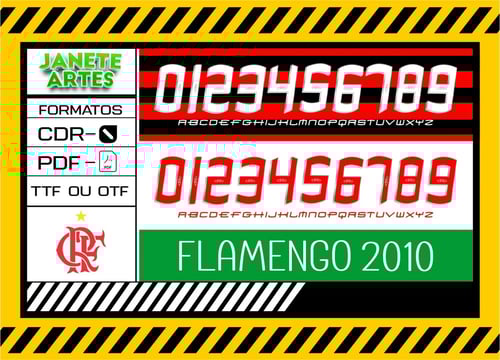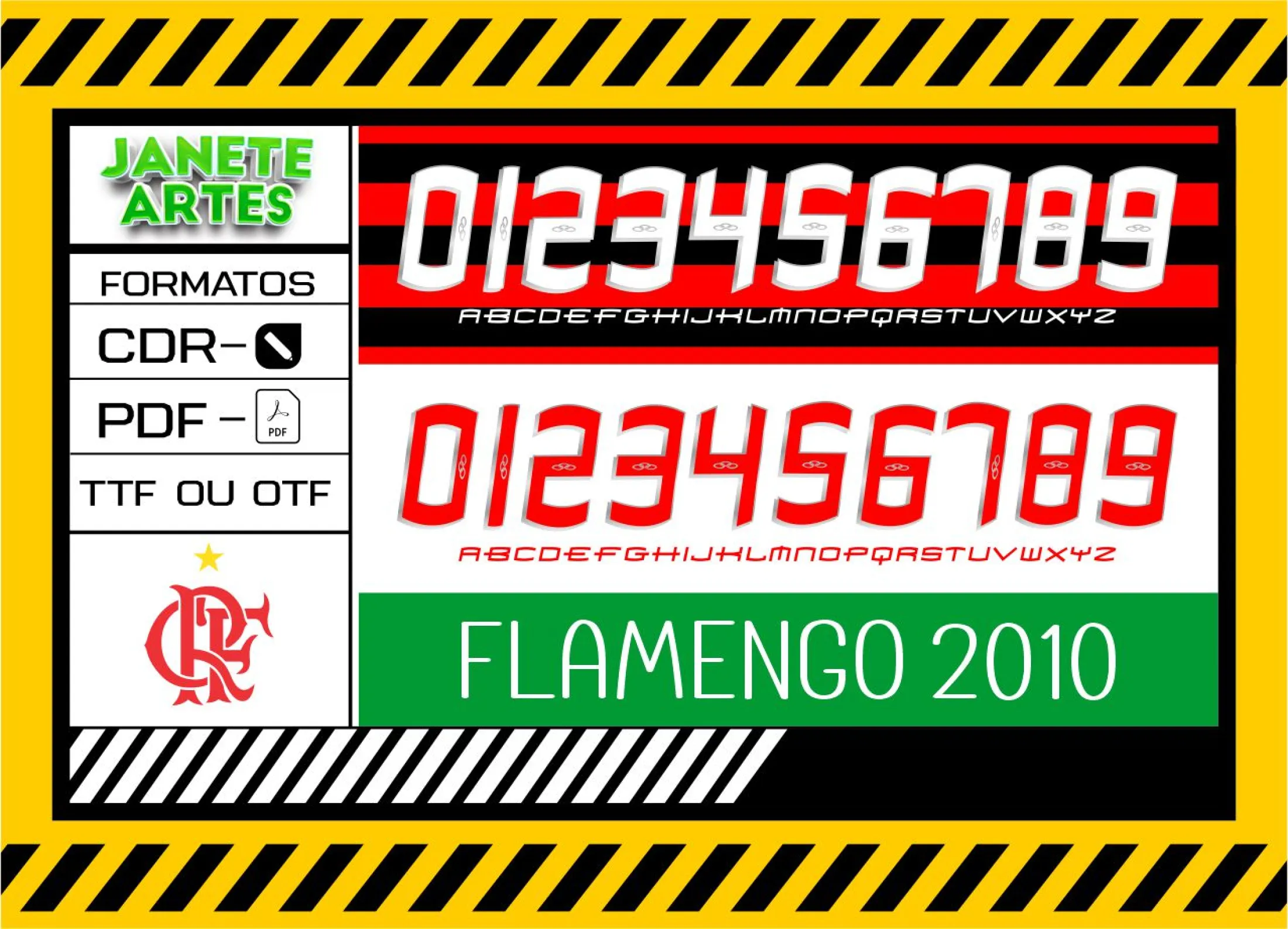
Fonte de Time Tipografia Flamengo 2010
Arquivo para criação da Fonte de Time Tipografia Flamengo 2010, perfeito para personalizar camisetas e camisas com o estilo único do Flamengo em 2010. Ideal para torcedores e eventos especiais.
Imagine um grupo de amigos reunidos para assistir a uma partida do Flamengo na temporada de 2010. A emoção da torcida, o som dos cantos ecoando pelo estádio, e o visual único da tipografia daquela época no uniforme. Foi um ano inesquecível para muitos fãs, onde a fonte do time marcou época, trazendo uma identidade forte e vibrante. Com esse arquivo, você pode reviver esse momento e personalizar suas camisetas com a mesma personalidade daquela temporada histórica.
• Ideal para criar estampas, personalizar camisetas, camisas e blusas com o estilo fiel da época.
Dicas para personalizar e combinar 🖌️
• Combine a fonte com as cores tradicionais do Flamengo: preto, vermelho e branco.
• Use a impressão em camisetas com fundo preto ou branco para maior destaque.
• Ideal para criar uniformes de torcida ou peças exclusivas para eventos esportivos.